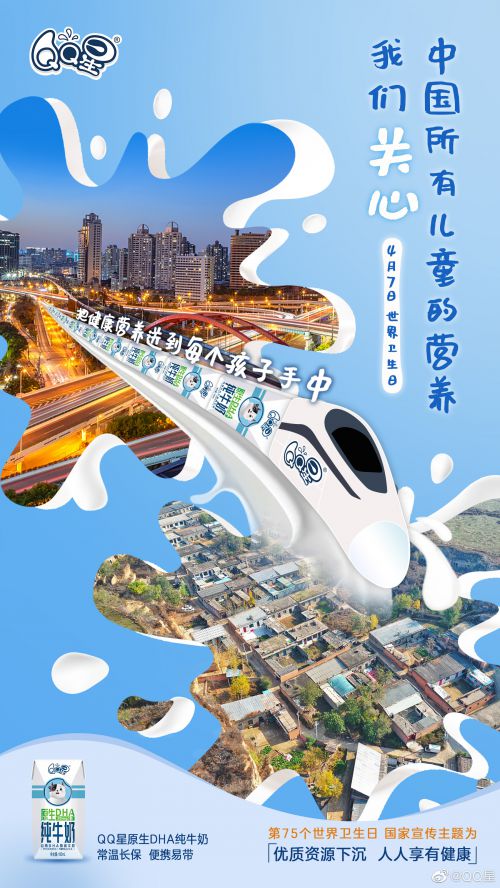
沐瑶随心手写体
沐瑶随心手写体是一款充满趣味的简体中文手写体字体,融合了卡通手写风格的灵动与手写文字的自然温度。作为免费商用字体,其修长的字形设计搭配居中的重心结构,展现出独特的视觉平衡感,中宫宽博的空间处理让文字更具呼吸感。 沐瑶随心手写体以圆润笔触为主,笔画粗细对比适中,连笔设计自然流畅,完美还原手写书写时的连贯性与灵动韵味。细节处保留手写特有的自然笔触与装饰元素,既不失卡通字体的活泼趣味,又兼具手写文字的亲切质感。 沐瑶随心手写体支持常规字符集,字重适中易读,适用于海报设计、社交媒体配图、手账排版、儿童读物等多种场景。作为免费商用字体,为设计师提供了灵活的创意选择,让手写风格的设计作品更具温度与个性。